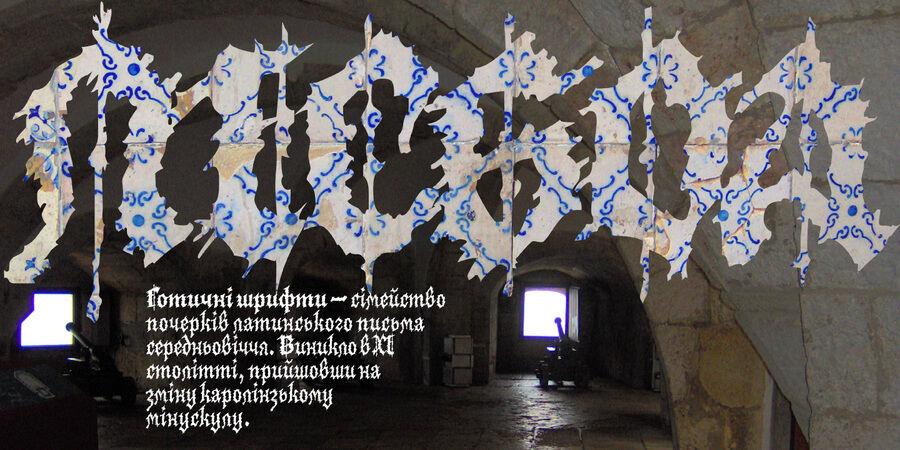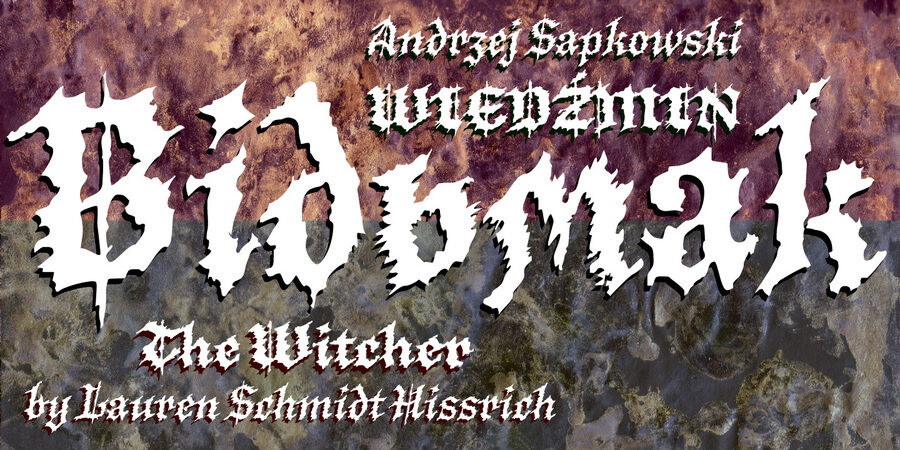
Неформальний готичний шрифт на всі випадки, коли він доцільний: від акциденції та реклами (музика, традиційні європейські напої та наїдки, молодіжні неформальні течії, історичні та фентезійні фільми тощо) до вишуканого книжкового оформлення (попри всю історичну екзотичність та «репаність» шрифт задовільно читається у текстових кеглях, створюючи при тому неповторний присмак середньовіччя). Окремо варто сказати про кирилку: зробити її органічною дуже непросто! Впродовж кількох століть з різним успіхом шрифтарі працювали над цим. Автором шрифту Lisboa зібрано та проаналізовано величезний матеріал та виявлені оптимальні рішення графем суто кириличних літер. Готика для Європи – це жива історія, як історичні споруди – подекуди це прикопані руїни, а подекуди цілком дієздатні та уживані будівлі, що грають значну роль у сучасному житті. Готичний шрифт – контрастний майже до всіх інших шрифтових груп, і за цією ознакою добре поєднується майже з ними усіма – від вишуканих чи неформальних курсивів до сучасних гротесків. Шрифт розробив Віктор Харик у 2019-2020 році.
Асоціації з сімейством шрифтів LisboaОсобистість і характер гарнітури:
гострий, історичний, ролевий, середньовічний, старовинний, казковий, артистичний, химерний, цікавий, оригінальний, традиційний, загадковий, складний, чарівний, готичний, майстерний, художній, естетичний, антикварний, королівський, пивний, колючий, різкий, грубий, епатажний, агресивний, емоційний, характерний, виразний, неохайний, андеграундний, гаражний, дивний, дикий, помітний, яскравий, живий, ремісничий, кустарний, крафтовий, страшний, небезпечний, зухвалий, макабричний, древній, декоративний, кущистий, рослинний, лісовий, кріповий, осінній, артізанальний, старомодний, самобутній, динамічний, колоритний, рукотворний, натуральний, творчий, чаклунський, магічний, божевільний, архаїчний, грунтовий, нервовий, запальний, жахливий, лякаючий, зловісний, злий, вампірський, цвинтарний, заразний, мертвий, пекельний, окультний, таємничий, моторошний, екзотичний, навіжений, радикальний, компактний, тісний